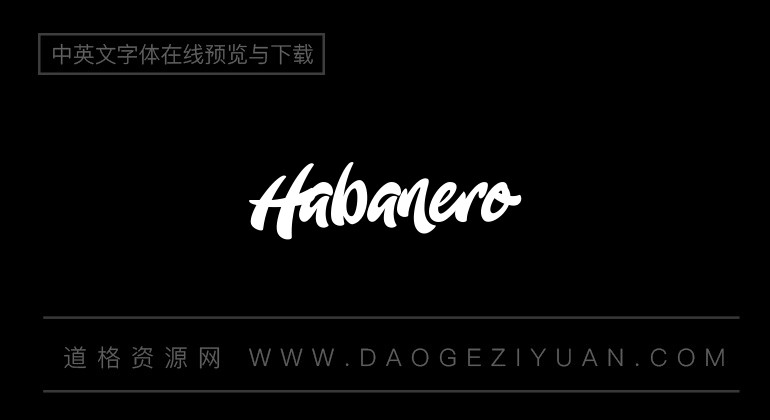
? Habanero 字体是一款由英国设计师 Tim Donaldson 设计的英文字体,它拥有清晰的笔画,拥有更多的可读性,可以帮助您在阅读和打印的时候更加轻松。它的字形比较大,即使在低分辨率的显示器上也能保持清晰。Habanero 字体有多种字重,可以满足不同的使用需求,比如标题、正文、抬头、标签等等。它适用于各种网页设计,也可以在报纸、杂志和书籍中使用。内容介绍
Habanero是一款非常不错的手写艺术字体,具有很好的视觉感,适合于文化类的宣传设计、商业类品牌的广告和产品包装设计以及个性化文字排版等较多场景。